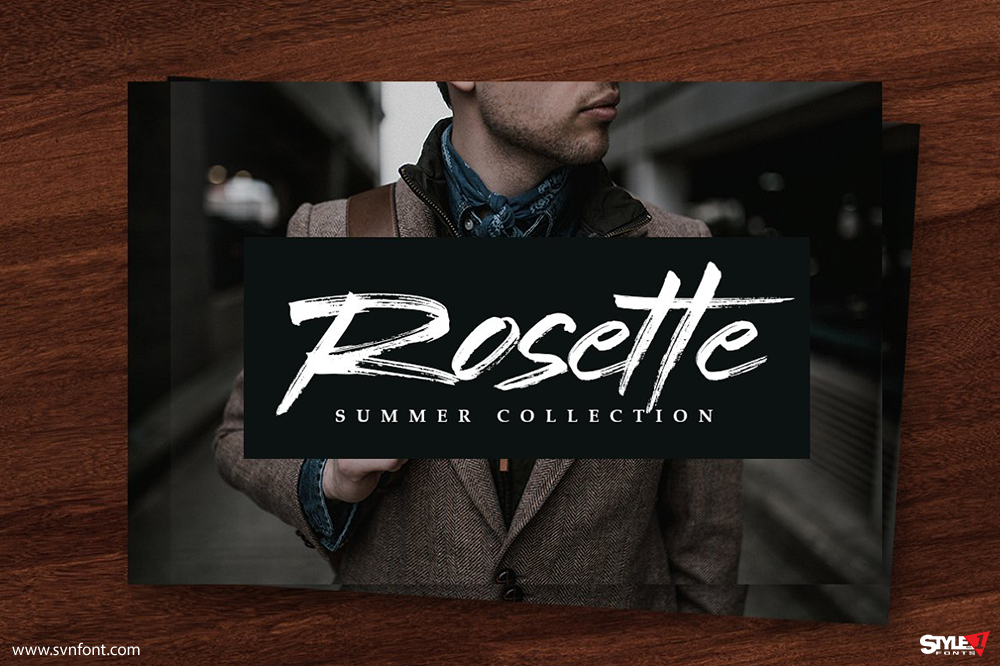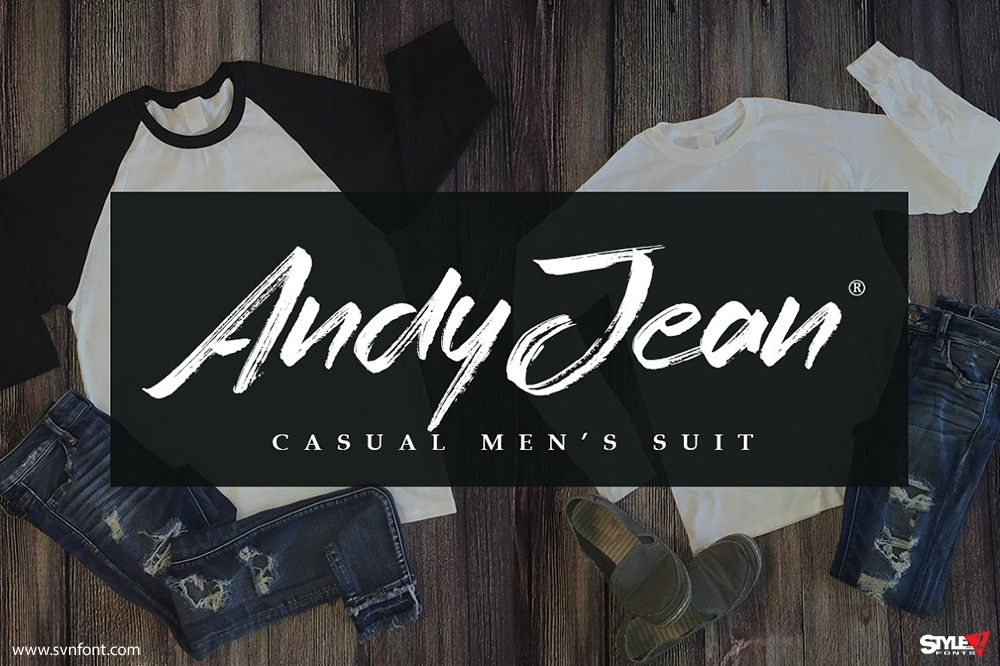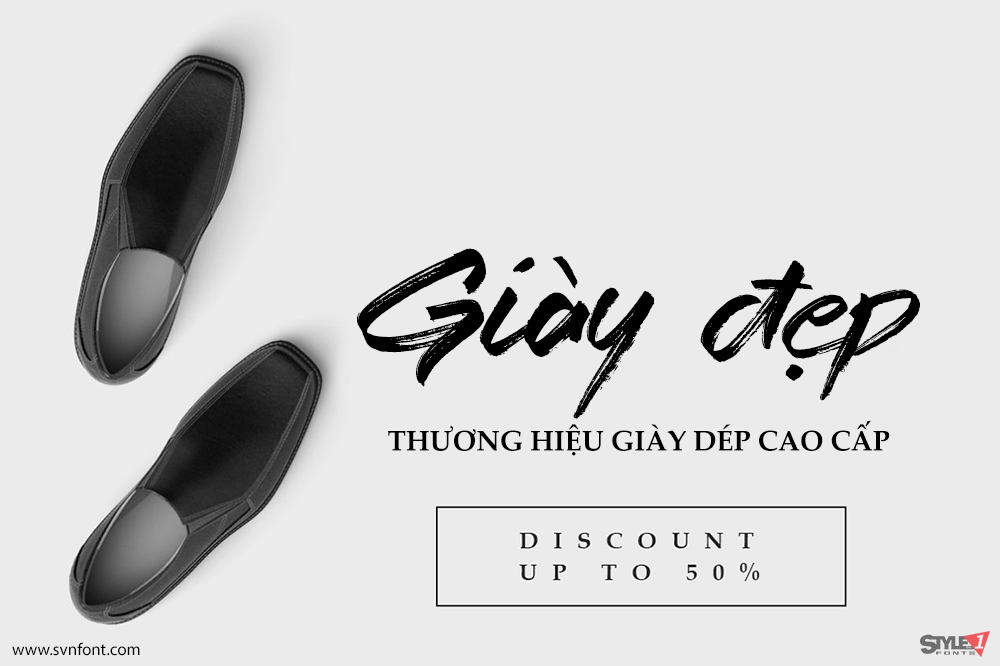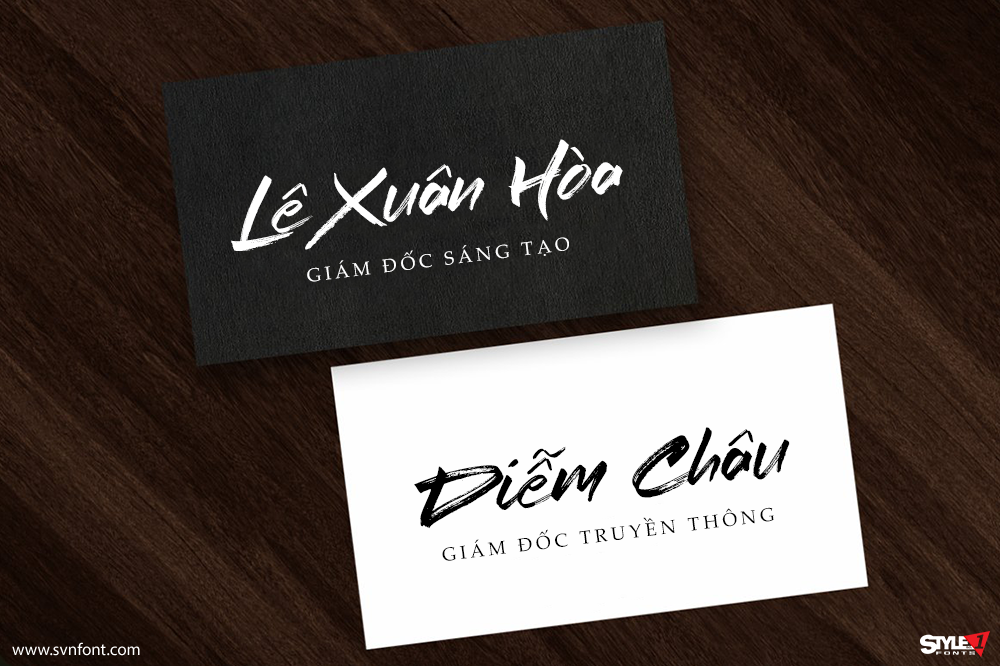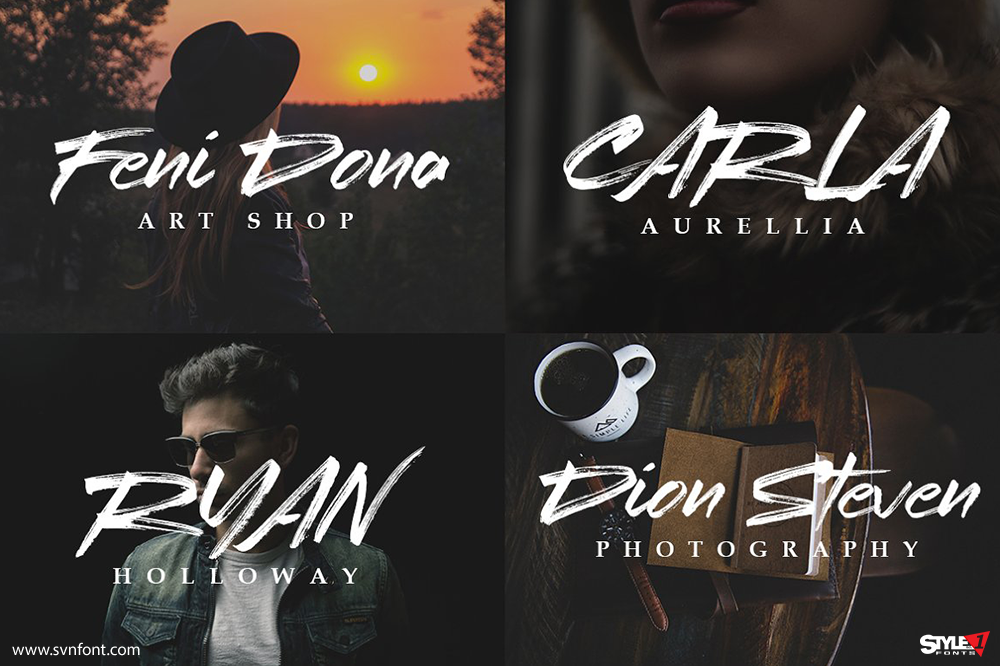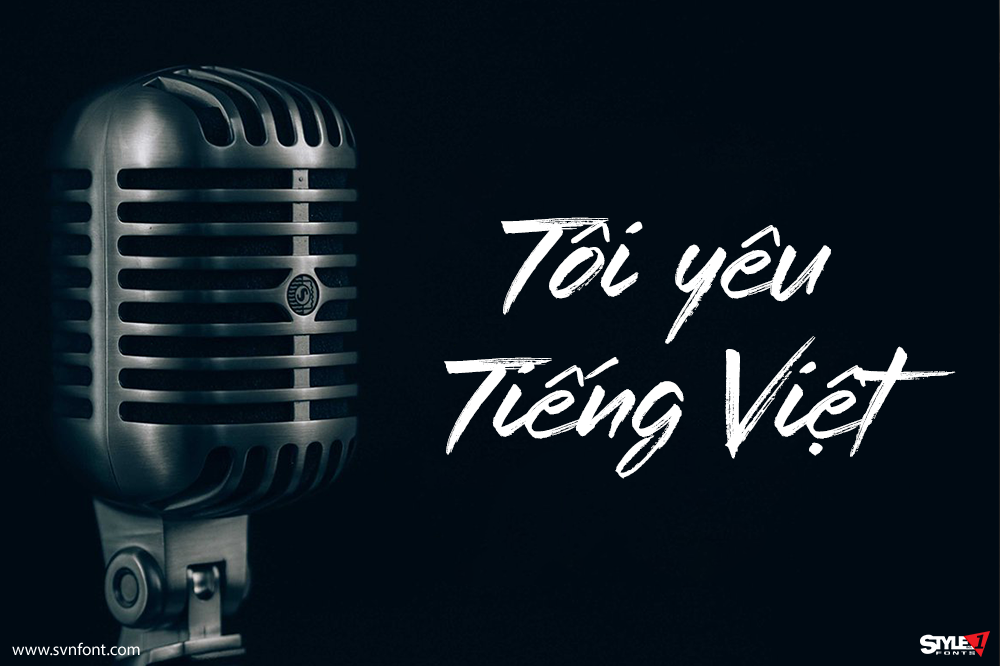
Redtowns là font được vẽ thủ công bằng bút brush trên giấy, mang lại cảm giác tự nhiên và giàu cá tính. Font rất phù hợp cho các dự án hiện đại như thời trang, chữ ký, watermark, nhiếp ảnh, poster, branding.
Redtowns còn đi kèm đường gạch chân trang trí có thể kết hợp hoàn hảo để tăng điểm nhấn thị giác. Dễ sử dụng, linh hoạt và khuyến khích sáng tạo — Redtowns sẽ giúp công việc thiết kế của bạn trở nên đơn giản và hiệu quả hơn.